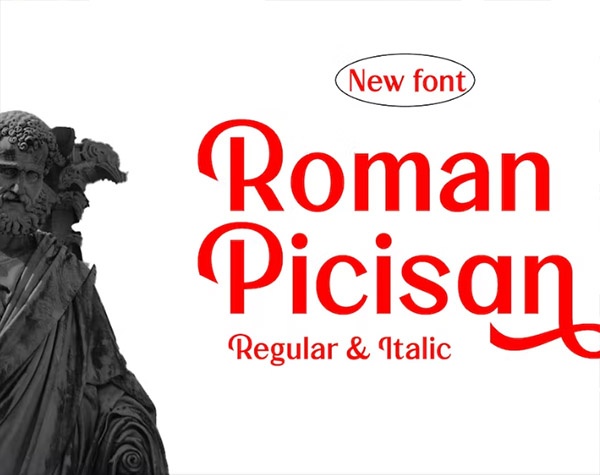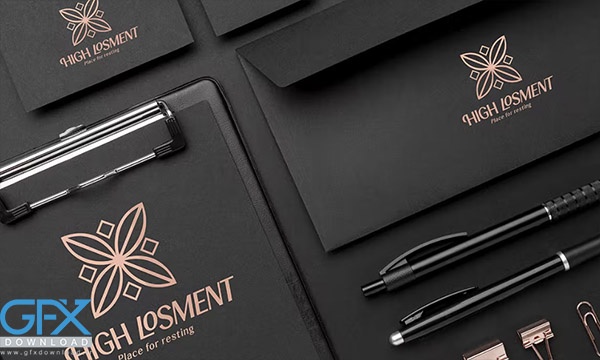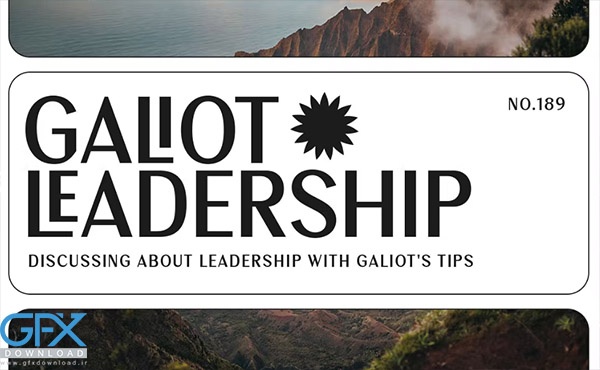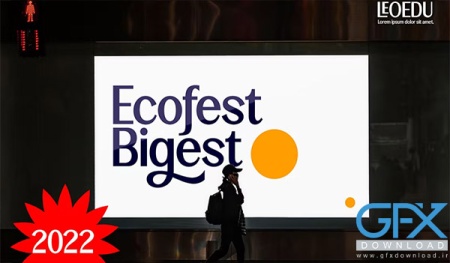
دانلود رایگان فونت رومی Roman Picisan
دانلود رایگان فونت انگلیسی رومی Roman Picisan
دانلود رایگان فونت رومی Roman Picisan یک فونت انگلیسی sans serif پیچیده و جذاب با طرح مد روز است. این فونت که مخصوص پروژه های لوکس، زیبا و زنانه طراحی شده است، برای ایجاد طرح های مدرن و شیک کاملا مناسب است.
فونت انگلیسی رومی Roman Picisan
• نام فونت: Roman Picisan
• حروف بزرگ و کوچک
• متناوب
• لیگاتورها
• عدد
• نقطه گذاری
• پشتیبانی چند زبانه